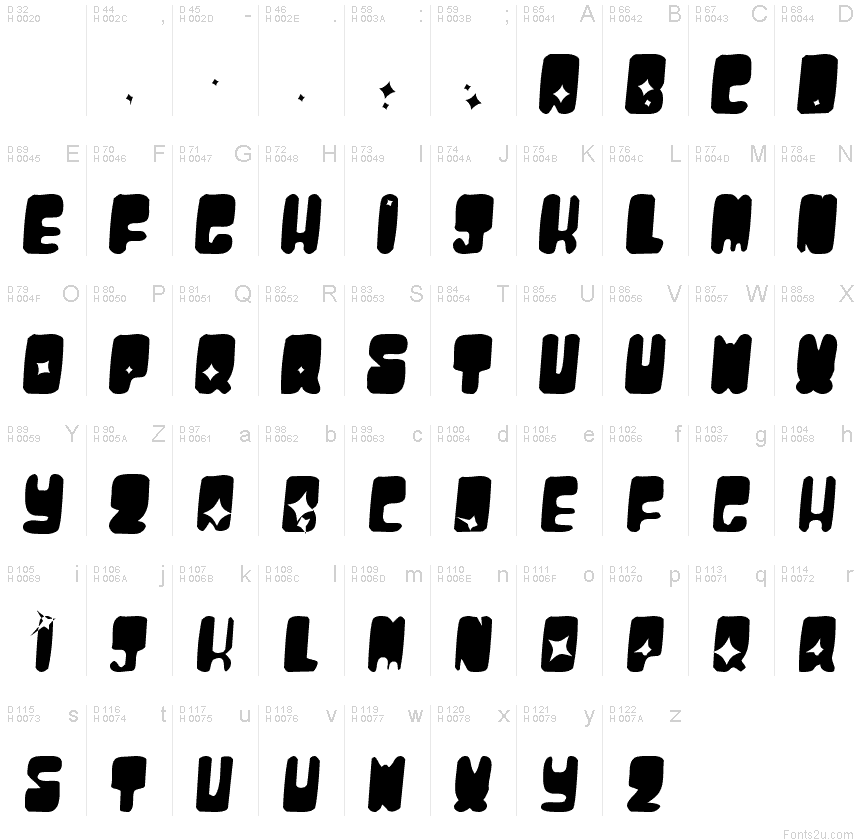
MoonPie Cadet von Font"a"licious Fonts ist eine kostenlose, groovige Display-Schrift, deren weiche, geschwungene Formen an ausgeschnittene Buchstaben von Postern aus den 70ern erinnern. Die füllige Statur und die charakteristischen sternförmigen Aussparungen lassen die Schrift weniger wie einfache Blockbuchstaben wirken, sondern wie ein kompaktes grafisches Muster.
Damit ist sie die perfekte Wahl für Album-Artworks, Party-Flyer, Ladenschilder, Sticker-Designs und große Überschriften mit einem Augenzwinkern Popkultur. Die kräftige Silhouette und die kleinen Sternchen-Details verleihen kurzen Texten auf Verpackungen oder Social-Media-Grafiken eine spielerische, siebdruckartige Energie, die in jedem nostalgischen Branding sofort ins Auge fällt.